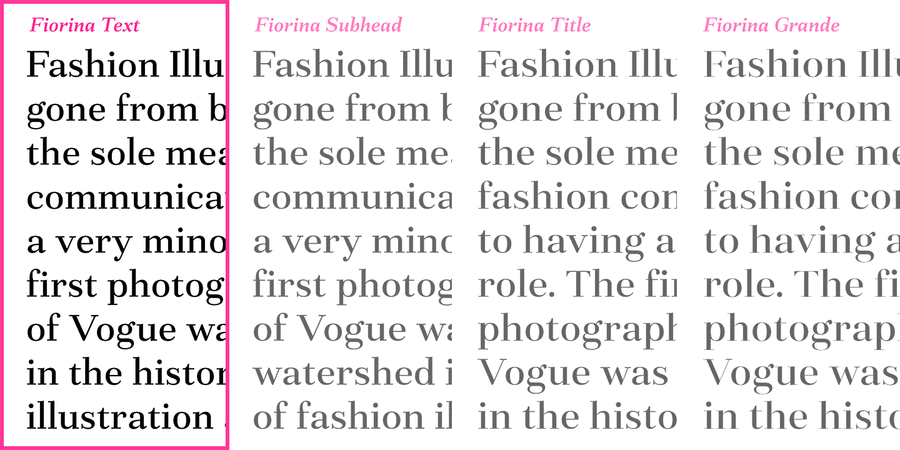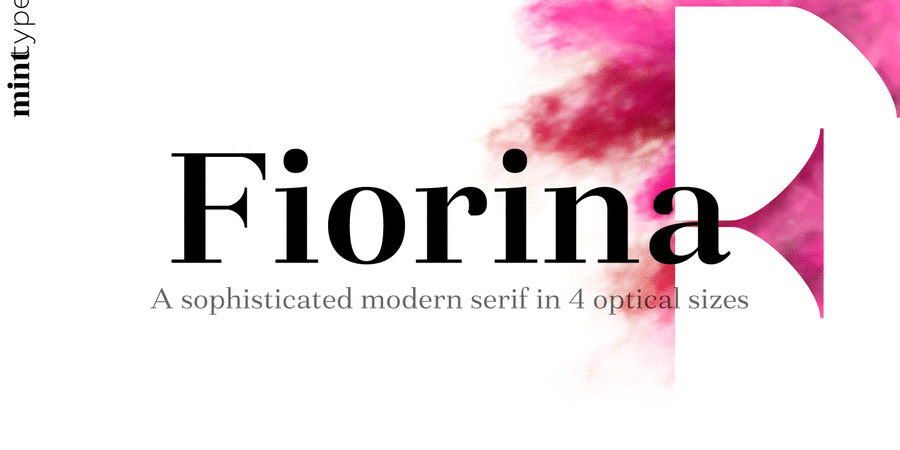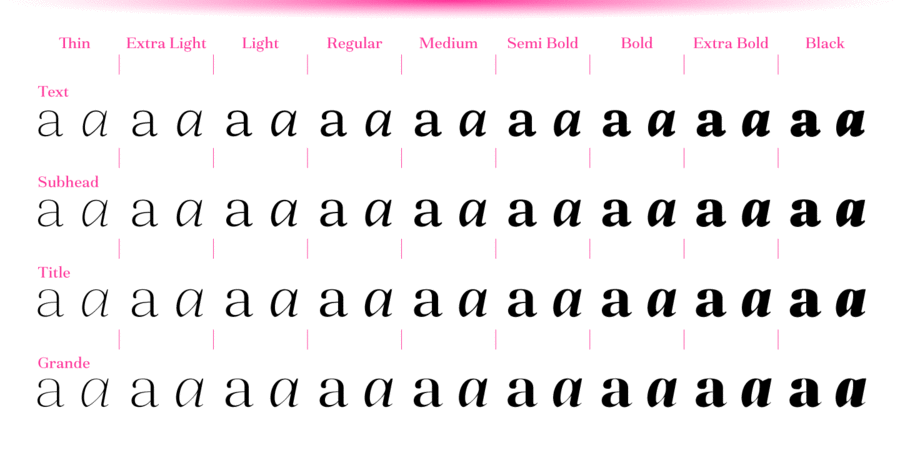
Опис гарнітури Fiorina TextТекстова версія шрифту з помірним контрастом. Fiorina – це антиква нового стилю, що складається з 72 накреслень. Шрифт створено в 4 оптичних розмірах: від текстового з помірним контрастом до надконтрастного Grande. Кожен з 4 наборів має 9 насиченостей з відповідним вишуканим курсивом. Загальна різноманітність накреслень робить Fiorina ідеальною гарнітурою для журналів. Набір ґліфів підтримує всі європейські мови на основі латинки, а також усіма основними мовами, в яких використовується кирилиця. Шрифтове сімейство також підтримує численні функції OpenType, включно з 6 наборами цифр, капітеллю, дробами, надрядковими й підрядковими індексами, порядковими числами й багатьма іншими можливостями. Шрифт розробив Андрій Константинов у студії Mint Type у 2020 році.
Асоціації з сімейством шрифтів Fiorina TextОсобистість і характер гарнітури:
тонкий, легкий, делікатний, рівний, гармонійний, технічний, сучасний, статичний, культурний, освічений, твердий, чіткий, різкий, модний, багатий, дорогий, худий, динамічний, серйозний, якісний, міський, витончений, свіжий, благородний, елегантний, комільфо, ввічливий, тактичний, формальний, стабільний, солідний, стійкий, спокійний, переконливий, класичний, інтелігентний, гордий, виразний, мотивуючий, відповідальний, яскравий, авторитетний, значний, важкий, щільний, помітний, активний